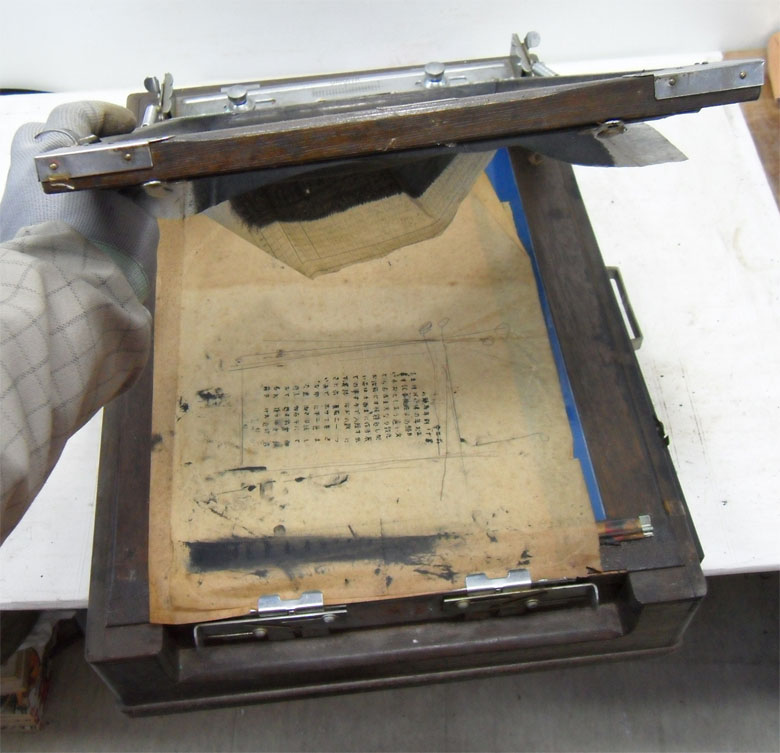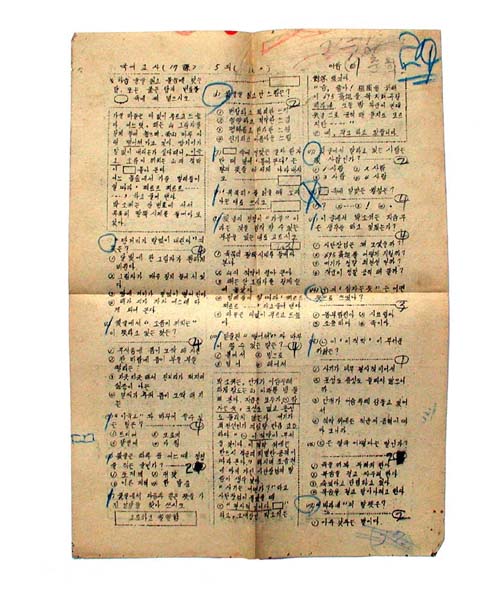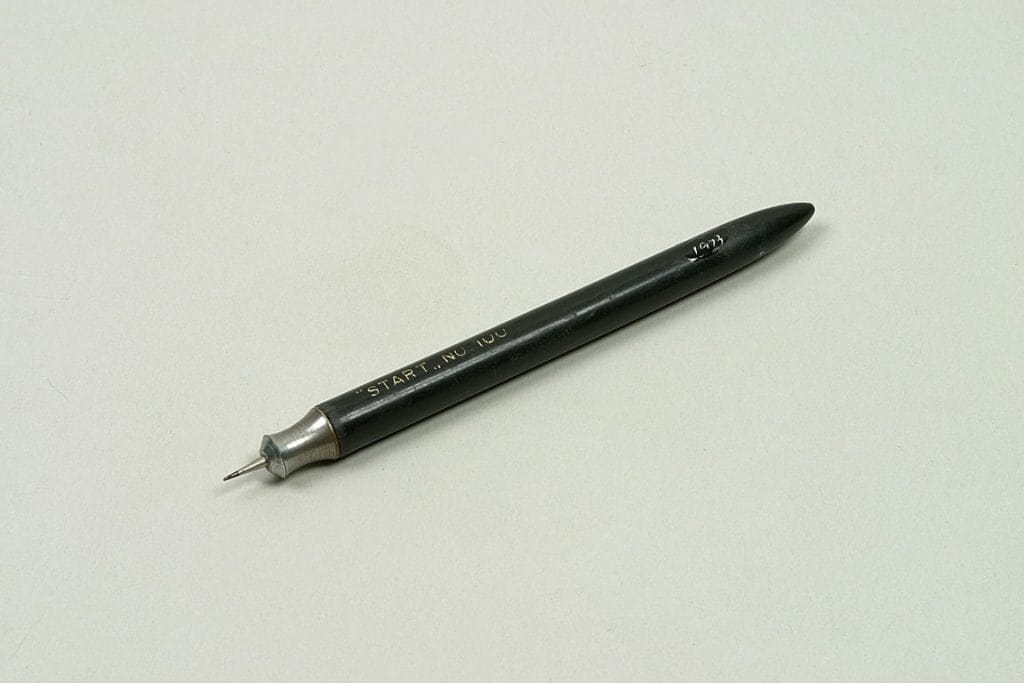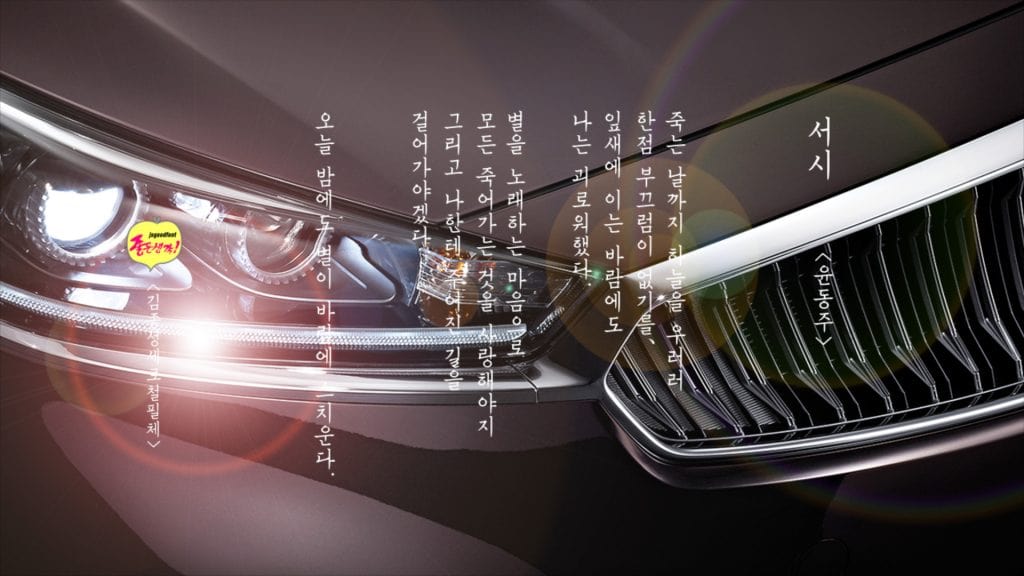
[note]● 어린 시절 기억[/note]
시골 가난한 국민학교 (지금은 명칭이 초등학교로 바뀠다)를 졸업하면 부모님을 도와 농사일을 하거나 강가에 나가 조개잡이를 하거나 아니면 타향에 나가 공장에 돈 벌러 나가야 할 처지지만 그래도 부모 덕분에 중학교를 가게 되는 학생들은 방과 후 교실에 남아 과외수업을 할 수가 있었다. 물론 선생님께서는 생활용돈을 벌기위한 수단이기도 했다. 공부가 끝나면 선생님께서 나를 남으라고 하신다. 등사 일을 도와 달라는 것이다.
등사란 기름 먹인 원지를 철판(철필로 원지에 글을 쓰면 철판과 철필이 부딪치는 소리가 ‘가리가리’하는 소리가 난다. 그래서 일본인은 ‘가리방’이라고 부른다 )에 올려놓고 철필로 끍어 글씨를 쓴 뒤 이 원지를 등사판에 붙이고나서 시커먼 콜타르 같은 잉크 묻힌 롤러를 굴리면 종이에 글자가 찍혀 나온다. 나무로 짜 맞춘 액자 같은 판을 흔히 ‘등사판’이라고도 부른다. 오늘날 컴퓨터로 출력한 문서까지도 ‘유인물(油印物)’이라 부르는데, 이 말은 바로 기름잉크 묻은 롤러를 밀어 등사판으로 인쇄한 문서라는 뜻에서 연유한 것이다.
선생님께서 시험문제를 미리 만들어 놓고 혼자서 롤러를 밀고 종이를 한 장 빼내고, 또 밀고 빼내고… 하다보니 검은 잉크가 시험지에 묻어 지저분해지고, 시간도 많이 걸리니까 누군가 옆에서 종이를 한 장씩 재빨리 빼내는 보조 역할이 필요한 것이다. 내가 그 보조원을 하면서 슬쩍 시험문제에 뭐가 나왔다는 것을 다 알게 된다. 당연히 늘 점수가 좋았다. 친한 친구에게 무슨 문제가 나왔다는 것도 살짝 아르켜주고 사탕도 얻어 먹기도 했다. 지금 같으면 어림없고 큰 일날 일이다. 그러나 그 시절에는 시골학교에서 자연스런(?) 일이고 선생님께서도 날 믿으니까 그 일을 맡겼는지도 모른다.
학창시절 시험 문제지부터 가정통신문까지, 학교에서 나눠준 거의 모든 문서는 이렇게 모두 등사기로 찍은 것이었다. 중학교에 들어가서도 등사지에서 풍기는 등사 잉크의 진한 석유 냄새를 잊지 못한다. 시험 시간에 감독 선생님이 나누어준 시험지를 받으면 글자가 잘 안 보이는 부분이 있다. 그러면 감독 선생님은 가장 또렷하게 인쇄된 문제지 한 장을 가지고 들어와서는, 글씨가 잘 안 보인다는 학생들 책상으로 일일이 다가가서 가르쳐 줬다. 예쁜 여선생님이 남학생반에 시험 감독으로 들어오기라도 하면 “글자가 안 보입니다”라고 엄청나게 많은 학생들이 손을 들었던 풍경은 잊을 수가 없다.
고등학교 여름방학 때, 초등학교 때의 친한 친구집에 놀러 간 적이 있었다. 그 친구는 원지에다 철필로 열심히 글을 쓰고 있었다. 교회에 다닌 그 친구는 교회 업무에 대한 내용을 쓰기도 하고 어떤 때는 시험문제을 쓰기도 했다. 무슨 시험문제냐 물으니 학교시험 문제라고 하며 아르바이트 일을 하며 용돈을 번다고 했다. 그러고는 나 보고 한 번 해보라는 소개도 해 주었다. 늘 방 안에 쪼그려 앉아 글쓰는 것이 너무 답답한 것 같아서 안 하겠다고 했다.
[note]● 철필과 한글 인연[/note]
나는 군행정병으로 36개월 복무하면서 챠트 작성도 많이 했고 원지에 철필로 끍어 쓴 문서를 등사기에 밀어 각 부대에 발송하거나 게시하는 일을 주로 했다. 그것이 철필과의 인연의 시작이었다. 제대 후 옥외광고 간판업을 직업으로 삼으면서 글자는 나의 생업이자 수단과 방법이 되었다. 간판 글씨나 현수막 글씨는 직접 도안하여 제작하며 소비자의 기호나 요구사항에 따라 서체를 디자인해야하는 일을 하면서 간판장이로서의 긍지와 자부심을 갖고 한글을 예술적으로 아름다움을 표현하려고 나름대로 창작에 열정을 쏟았다.
철필글씨를 폰트로 만들다
세월이 흘러 컴퓨터가 보급되면서 컴퓨터문자커팅기가 보급되고 각종 한글서체가 입력되어 원하는 글자를 대량으로 생산하는 시대가 왔다. 그와 때를 맞춰 나도 한글서체를 개발해 보려고 시도를 했다. 여러번 좌절과 포기를 거듭하다 ‘박정희서체’를 개발하게 되었다. 그러나 잊었던 향수를 떠 올리며 추억의 등사기 글씨를 되살려 보고 싶었다. 손때 묻은 글씨가 그립기만 했다. 내 이름을 걸고 철필체를 완성하게 이르렀다. 한글 11,172자 모두 입력할 수 있는 ‘김종성가로철필체, 김종성세로철필체_V, 김종성세로철필체_Vm’이 그것이다.
개발한 이 서체는 내가 철판 위에 원지를 깔고 철필로 한 자 한 자 또박또박하게 쓴 글자의 재현이다. 지금은 잘 사용하지 않지만 당시에는 세로쓰기도 많이 했다. 세로글은 가로글과 달리 품격이 묻어나 보는 것만으로도 품위있고 우아하다. 세로쓰기는 무엇보다도 중요한 것은 세로 기준선을 잘 지키는 데 있다. 기준선 정렬을 지키지 않으면 글자가 들죽날죽하게 되고, 그렇다고 너무 정확하게 기준선을 따르다보면 딱딱한 느낌을 준다. 그래서 손글씨에서 세로 기준선을 맞추듯이 세로글도 자연스런 정렬 원칙을 세워 제작하였다. 세로글_V와 세로글_Vm의 차이는 일반문서에서는 세로글_V를 사용하고 영상자막프로그램인 프리미어나 에프터애펙에서 세로글 자막을 넣을 때는 세로글_Vm을 사용하도록 별도 제작하였다.
제작한 서체가 응용프로그램에 제대로 적용되는지 서체 활용도 테스트를 위해 한글 문서 프로그램인 한컴오피스를 비롯하여 그래픽 프로그램의 대명사 포토샵과 일러스트레이터 그리고 영상편집프로그램인 프리미어와 에프터이펙트에 시험한 결과 원활하게 적용됨을 확인하였다. 이 서체는 한국저작권위원회에 정식 소프트웨어 등록을 마쳤다.
[important]● 김종성철필체 감상[/important]
◆ 가로철필체로 자막을 넣은 유튜브 영상입니다. 화면에 어떻게 표현되는지 직접 눈으로 확인하실 수 있습니다.
◆ 이번에는 세로철필체로 자막을 넣은 영상입니다.
화면에 고정 된 명조체는 기아차광고 본래 서체이며, 아래로 펼쳐지는 서체는 필자의 세로철필체입니다.
두 서체를 비교하면서 감상해 보시기 바랍니다.
컴퓨터 보급이 늘어난 1990년대 초부터 등사판은 사라져갔다. 하지만 지금도 더러 골동품 가게에 보이는 등사판 위에는 잊지 못할 에피소드들이 끝없이 쌓여 있다. 어려운 시절, 배고픈 시절을 가난한 우리들과 함께한 물건이었다. 투박한 목제품이지만 오래오래 손때 묻혀가며 아껴 썼으며, 불완전한 물건이기에 오히려 더 많은 사연들이 빚어졌던 것 아닌가 한다. 컴퓨터 프린터나 복사기는 등사판보다 몇십 배 편리하기는 하지만, 40~50년 뒤 우리에게 잊지 못할 추억을 남기는 물건이 될 수 있을까 궁금하다.
역사적으로 볼 때 일제 식민지 시기 항일 독립투사들은 독립선언문을 등사기를 이용하여 복사해 전국 방방곡곡에 뿌렸으며, 광복 후 학생운동이나 반체제 투쟁 유인물 작성도 모두 등사기을 이용하기도 했다. 은밀한 장소에서 유인물을 작성하여 인쇄소를 거치지 않고 집안에서 보안을 유지할 수 있었던 것도 등사기의 역할이었다.